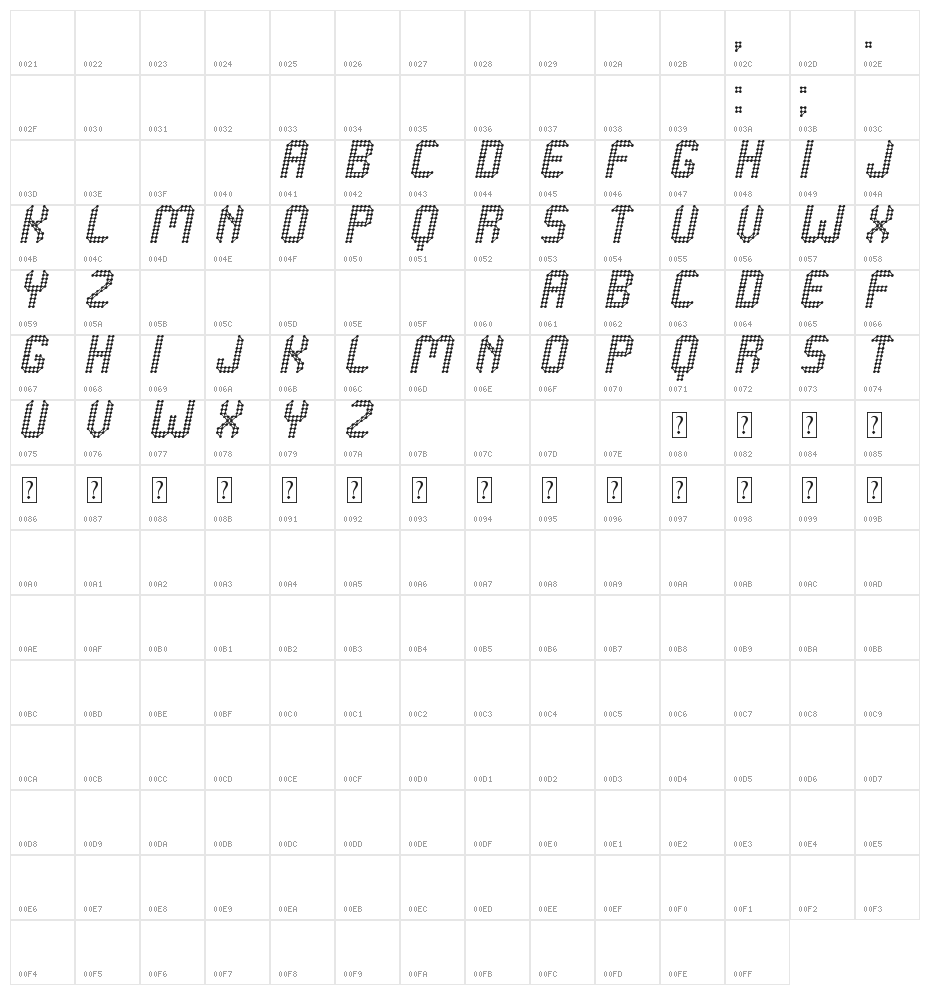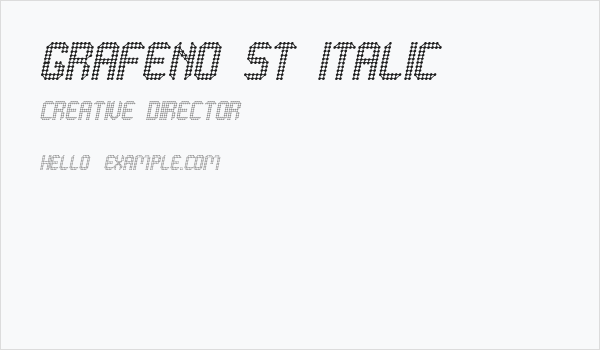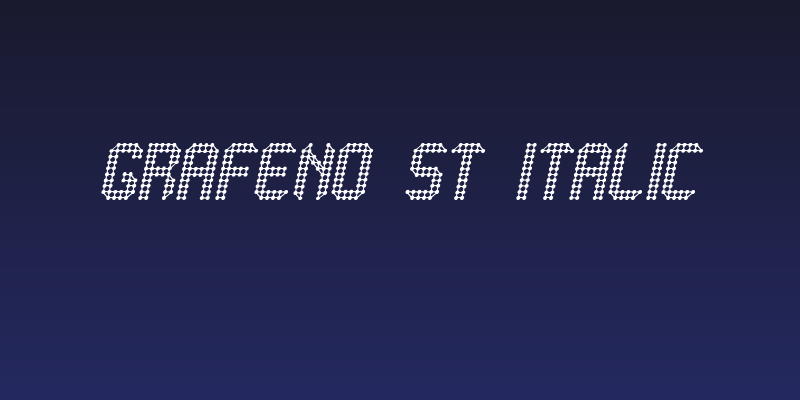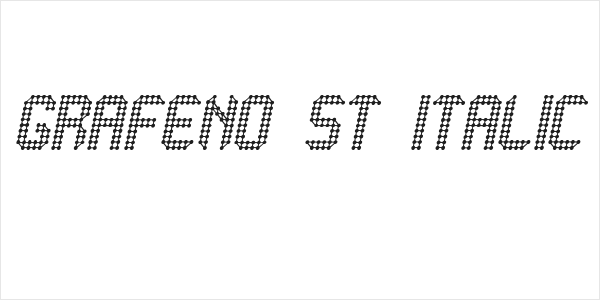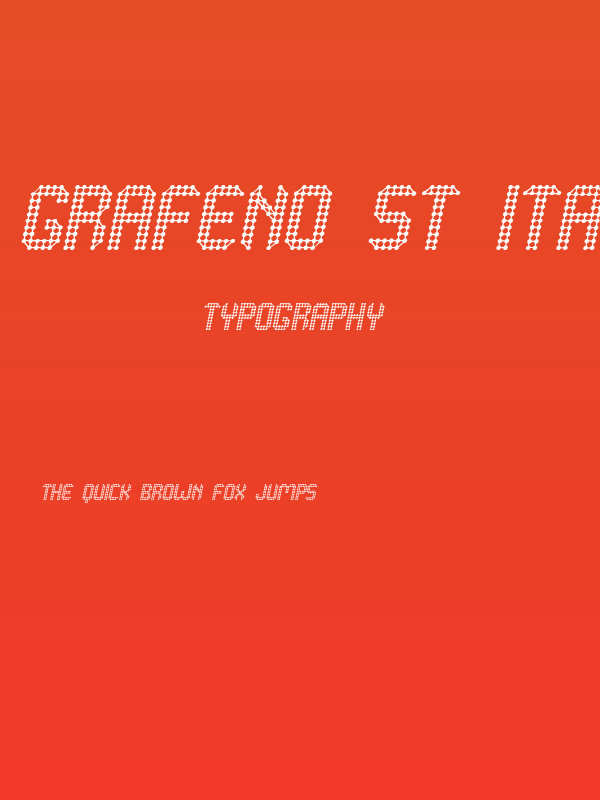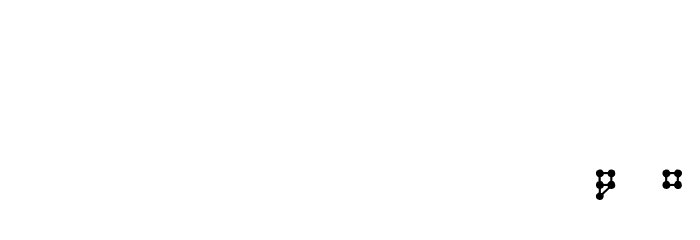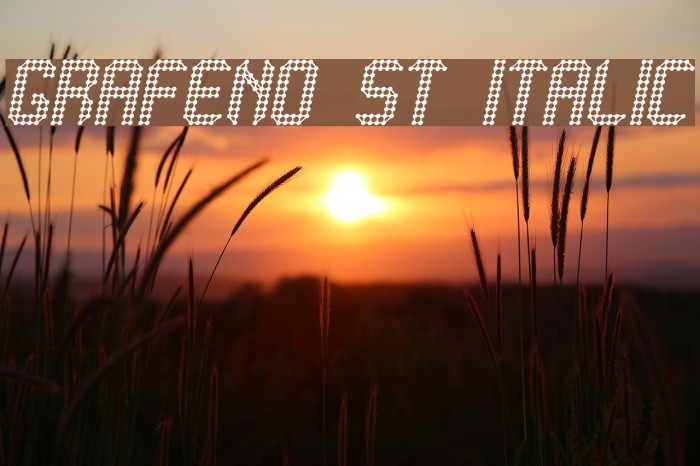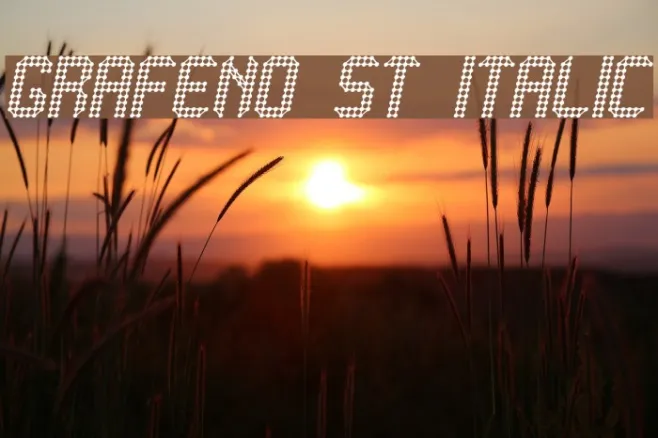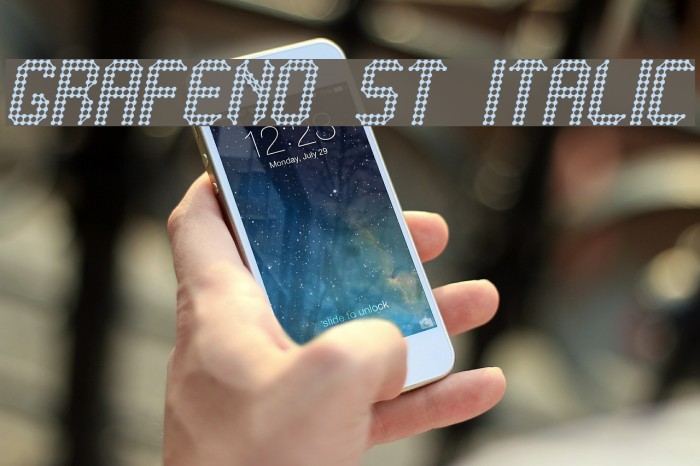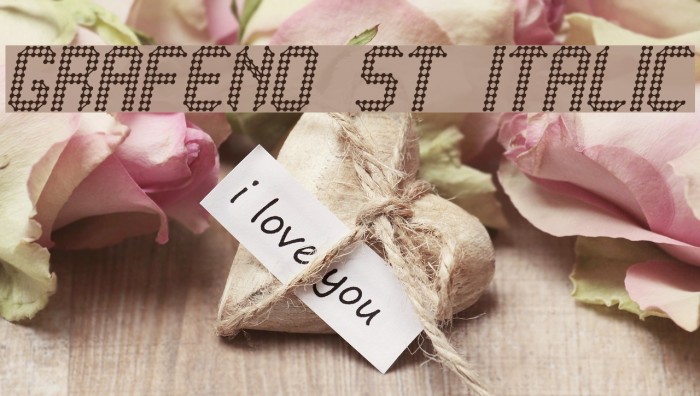
Grafeno St Italic Font
| Projets proposés | Ideal for tech-themed designs, futuristic branding, or any project requiring a modern and unique typeface. |